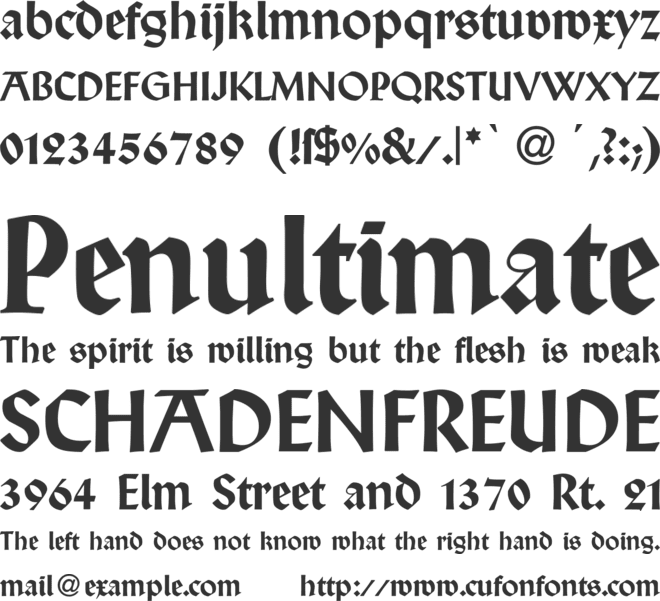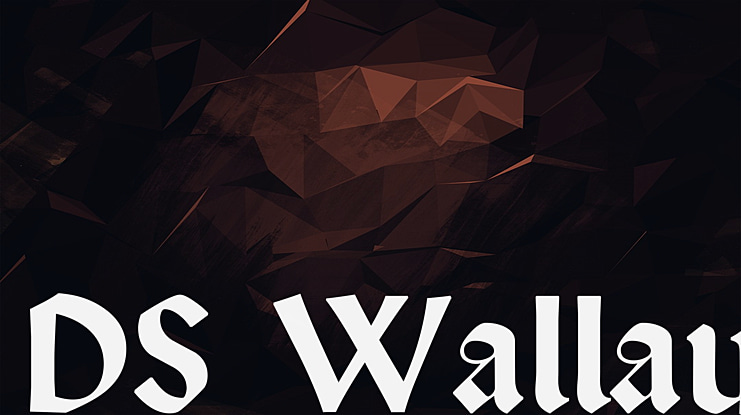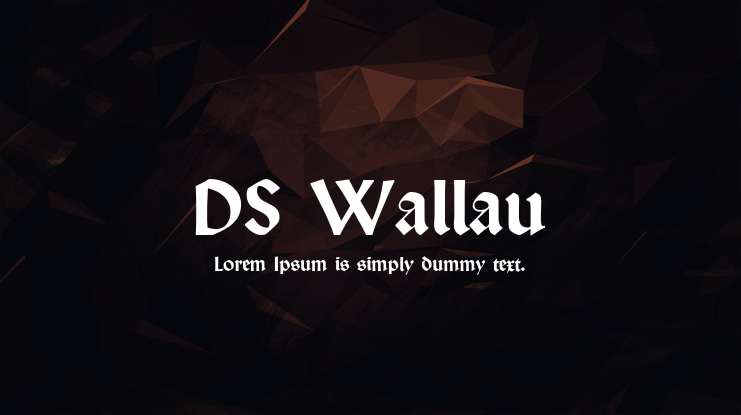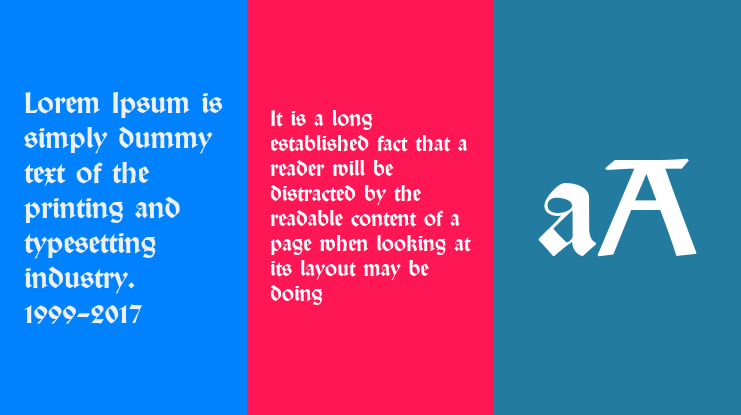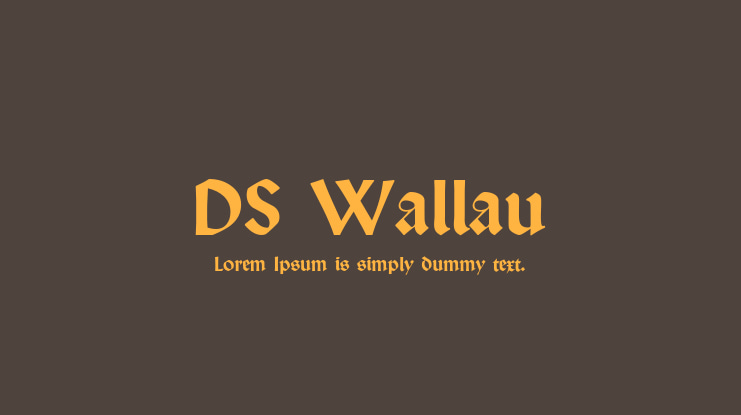
DS Wallau Font Family
Prof. Rudolf Koch (1925-1930)
Halbfette Wallau Rundgotisch mit unzialen Großbuchstaben von Prof. Rudolf Koch (1925-1930). Digitized and hinted by Dieter Steffmann, Kreuztal